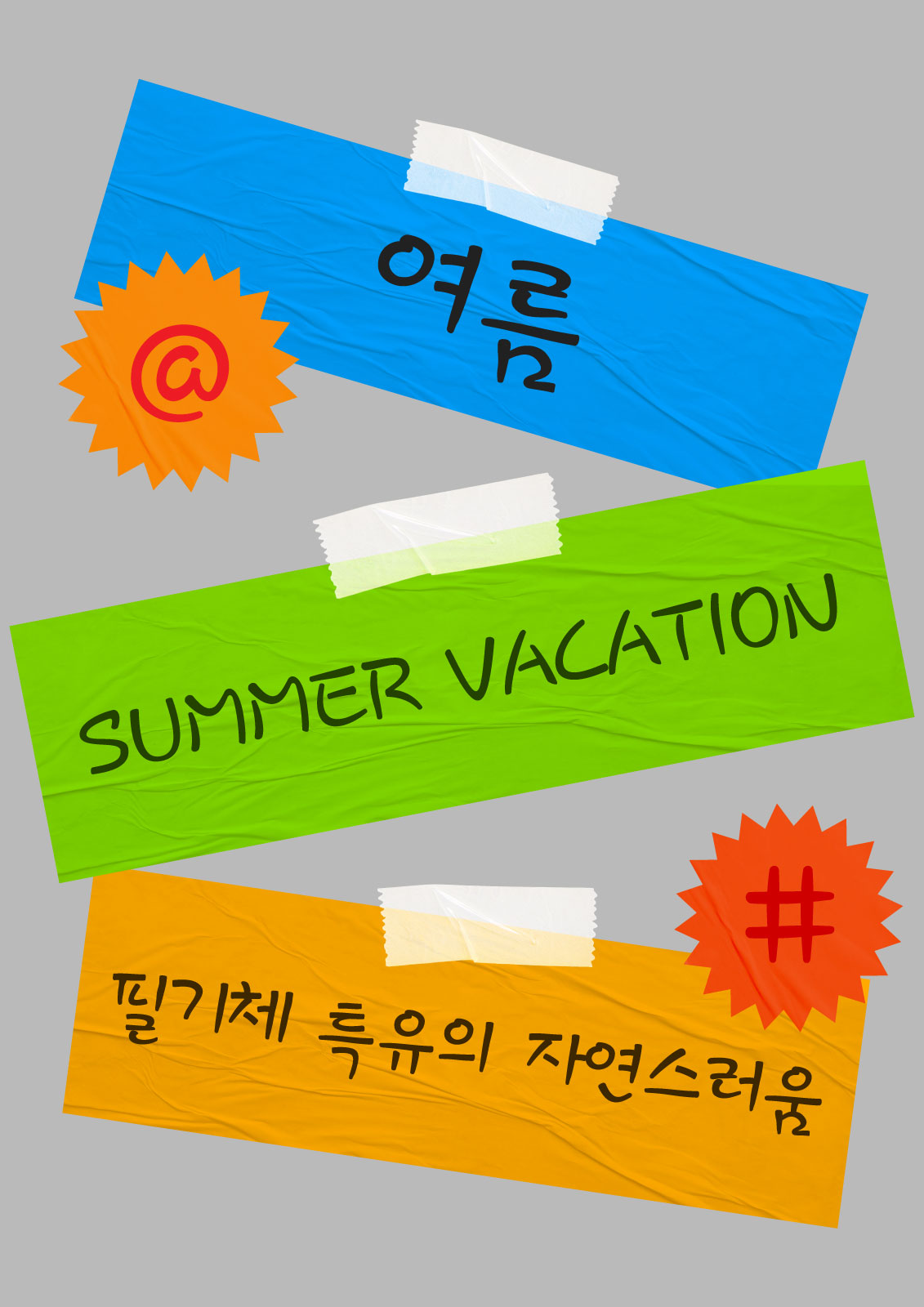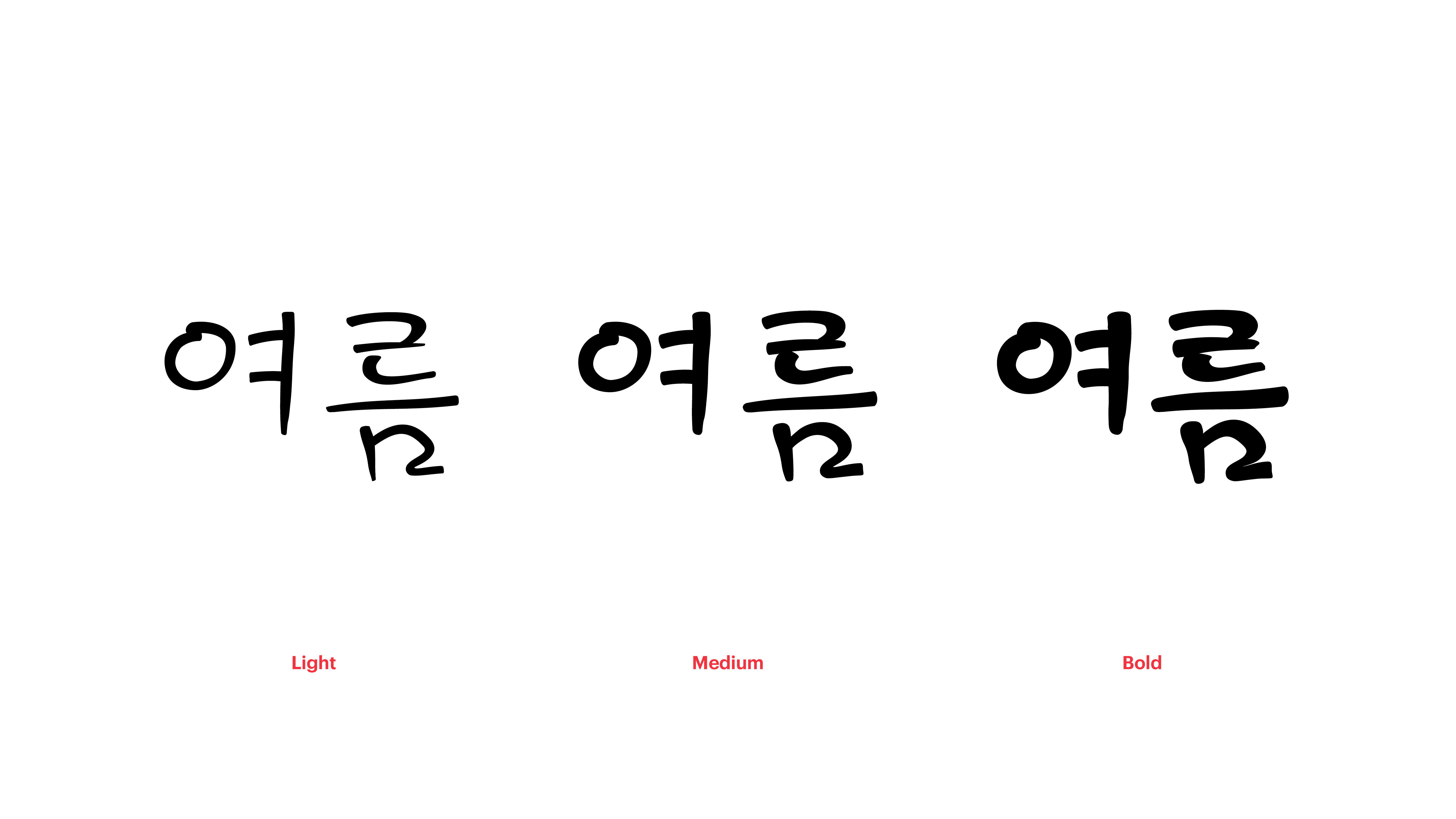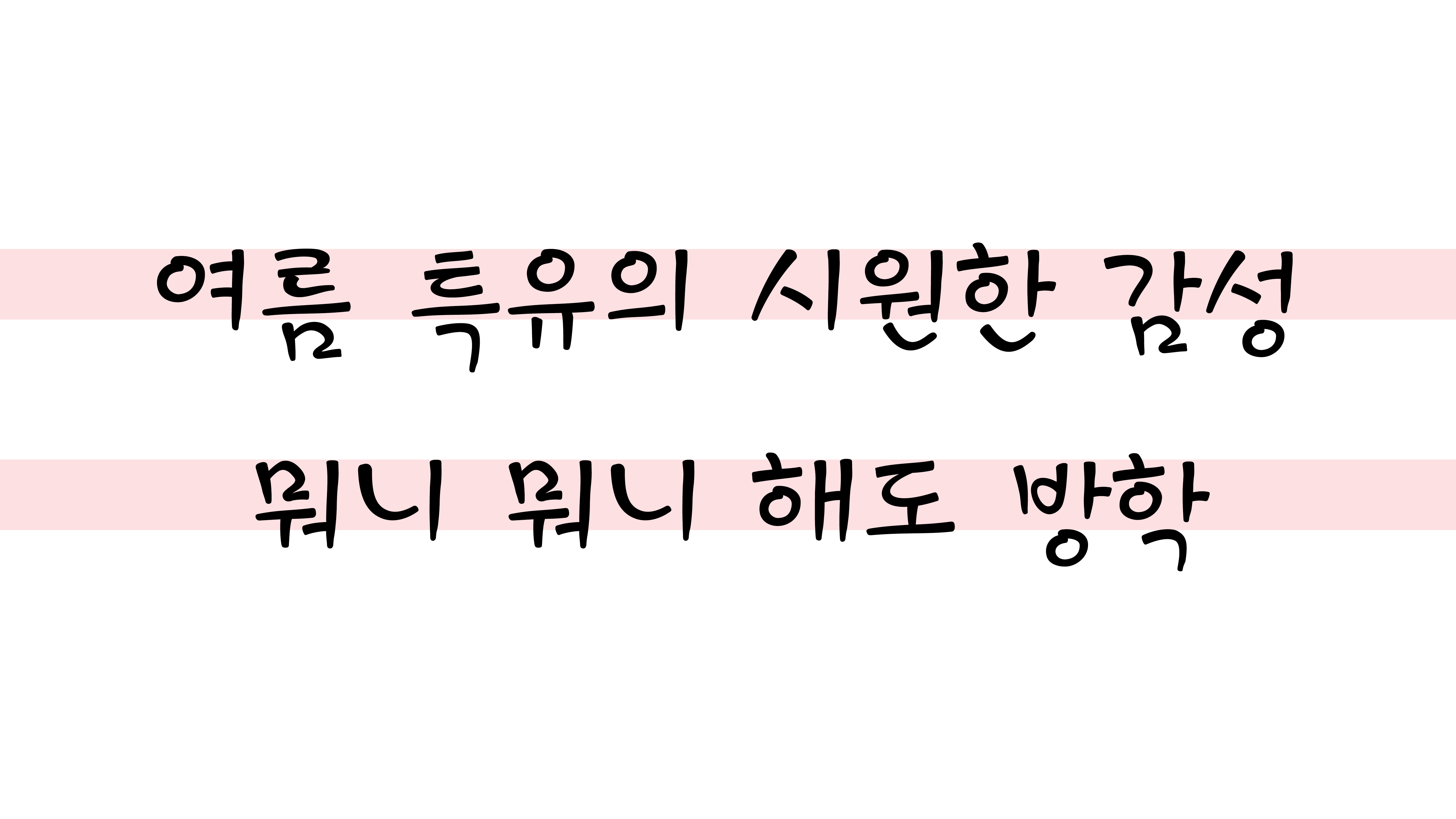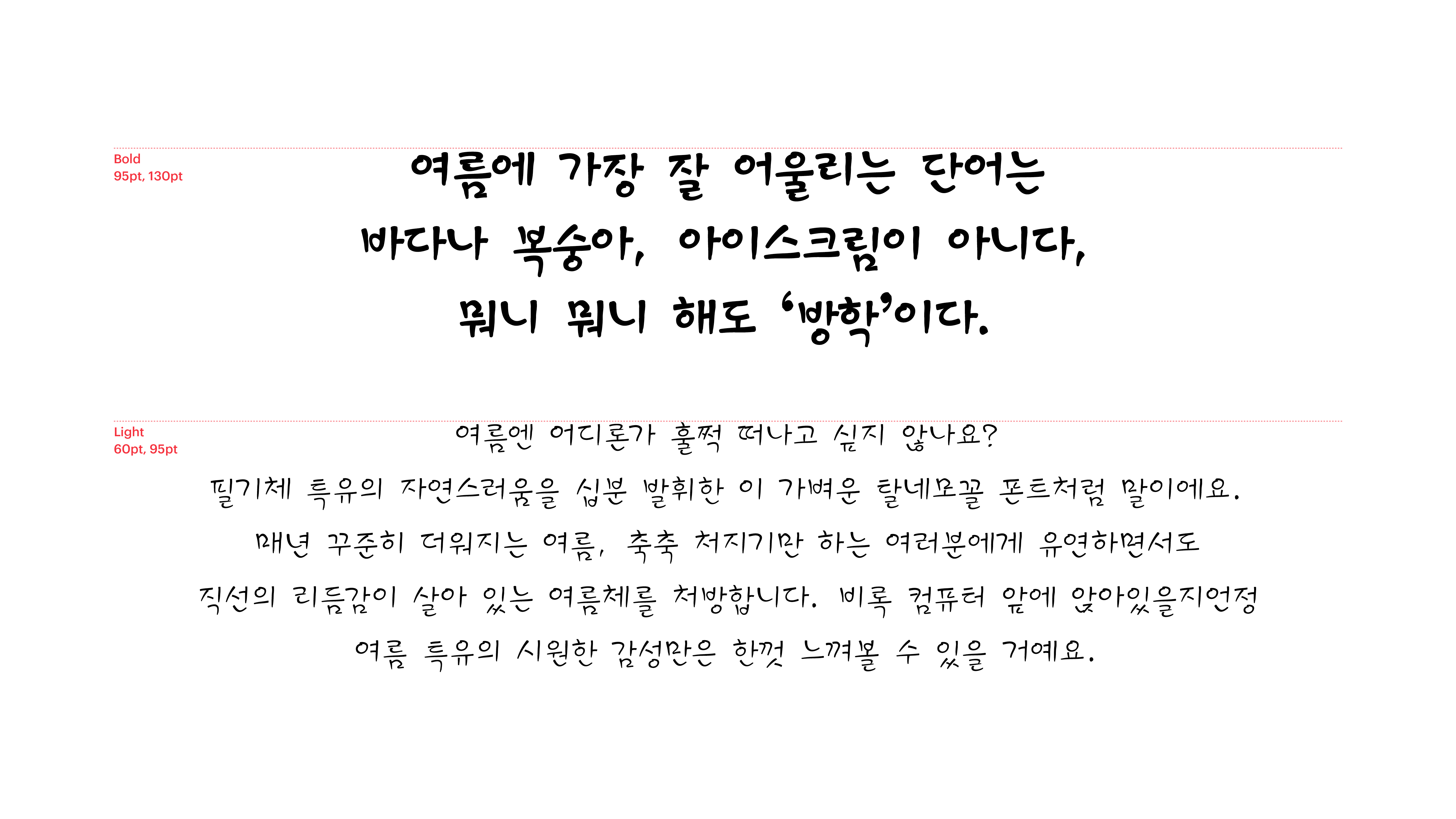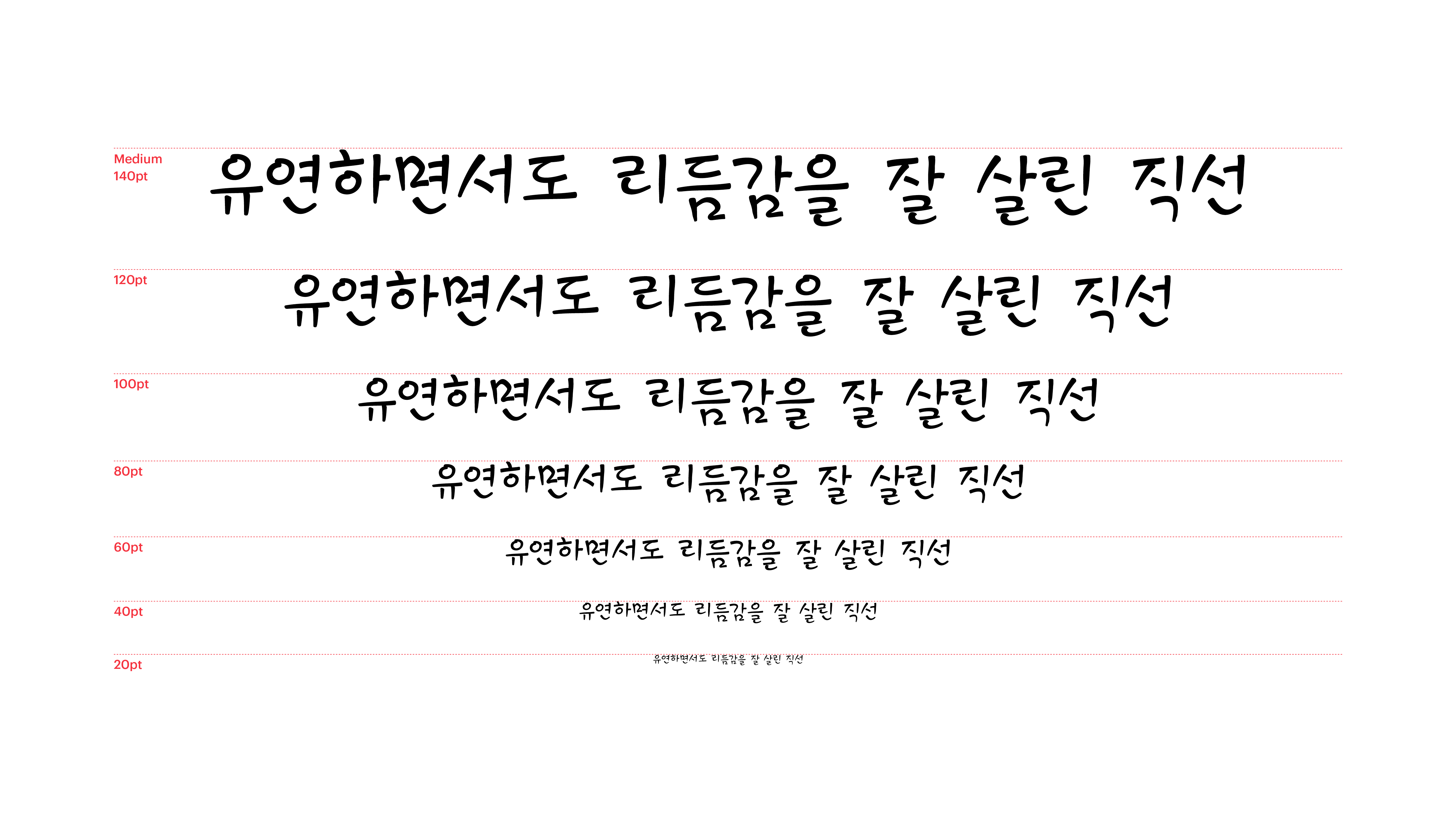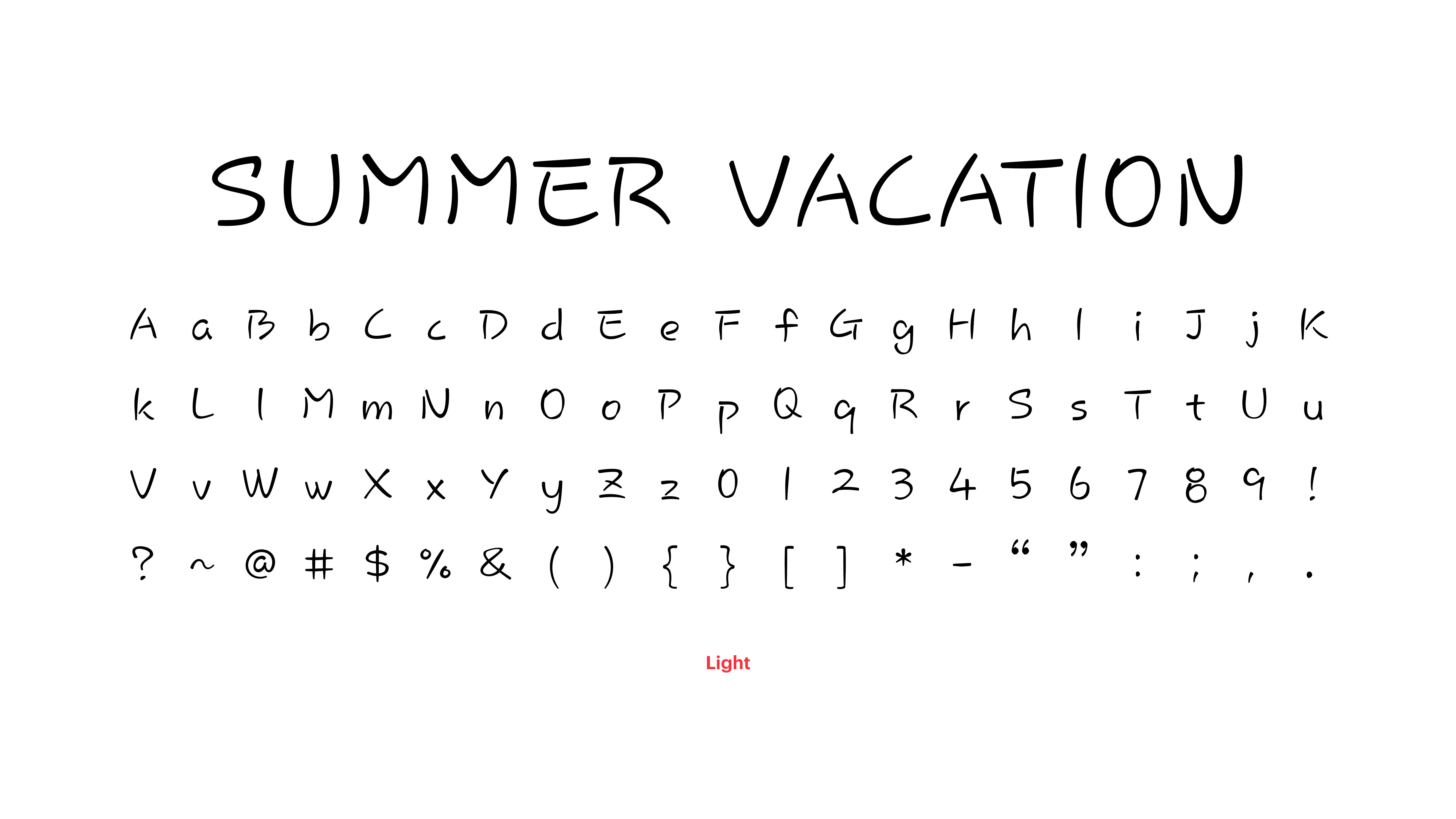
여름엔 어디론가 훌쩍 떠나고 싶지 않나요? 필기체 특유의 자연스러움을 십분 발휘한 이 가벼운 탈네모꼴 폰트처럼 말이에요. 매년 꾸준히 더워지는 여름, 축축 처지기만 하는 여러분에게 유연하면서도 직선의 리듬감이 살아 있는 여름체를 처방합니다. 비록 컴퓨터 앞에 앉아있을지언정 여름 특유의 시원한 감성만은 한껏 느껴볼 수 있을 거예요.
Yoon 여름